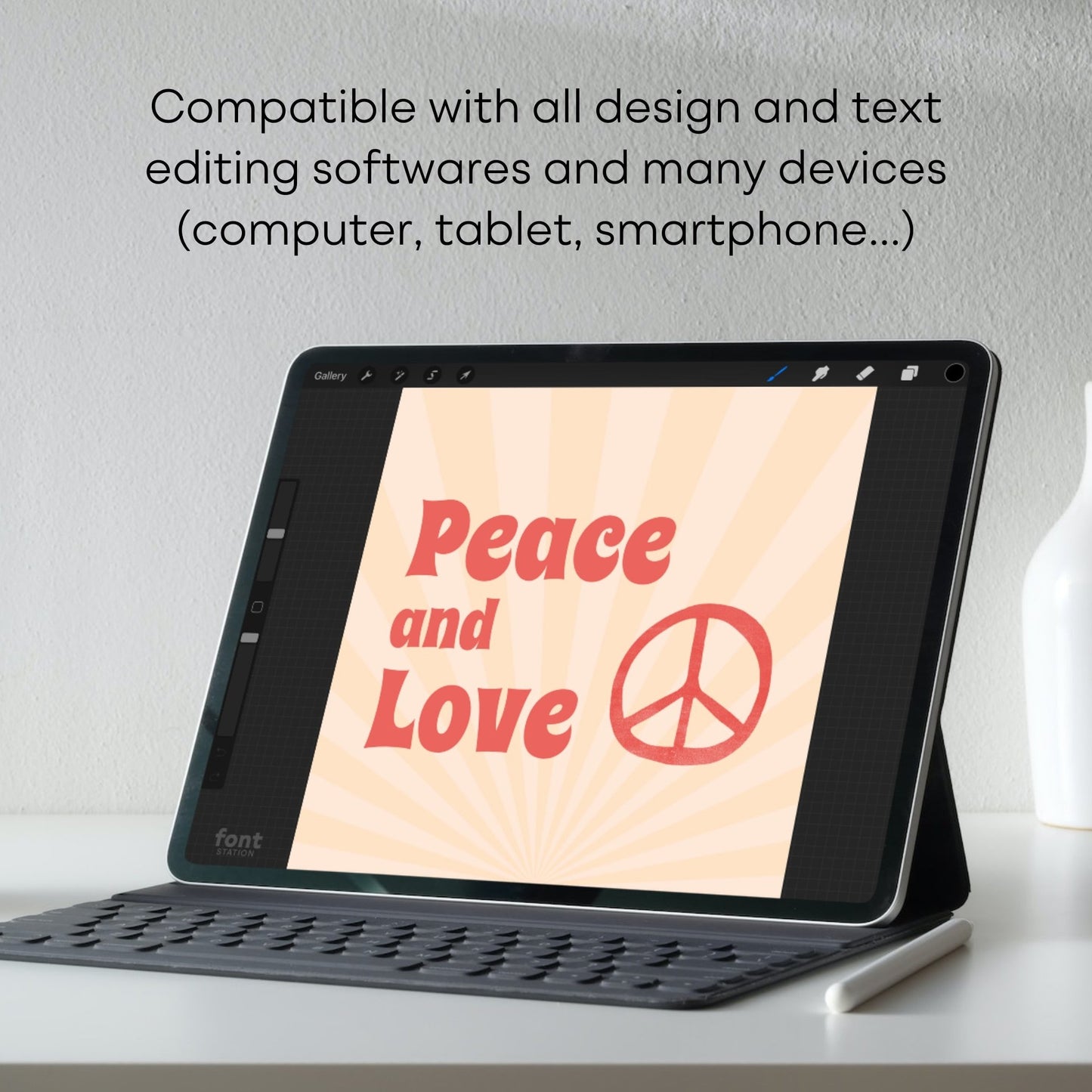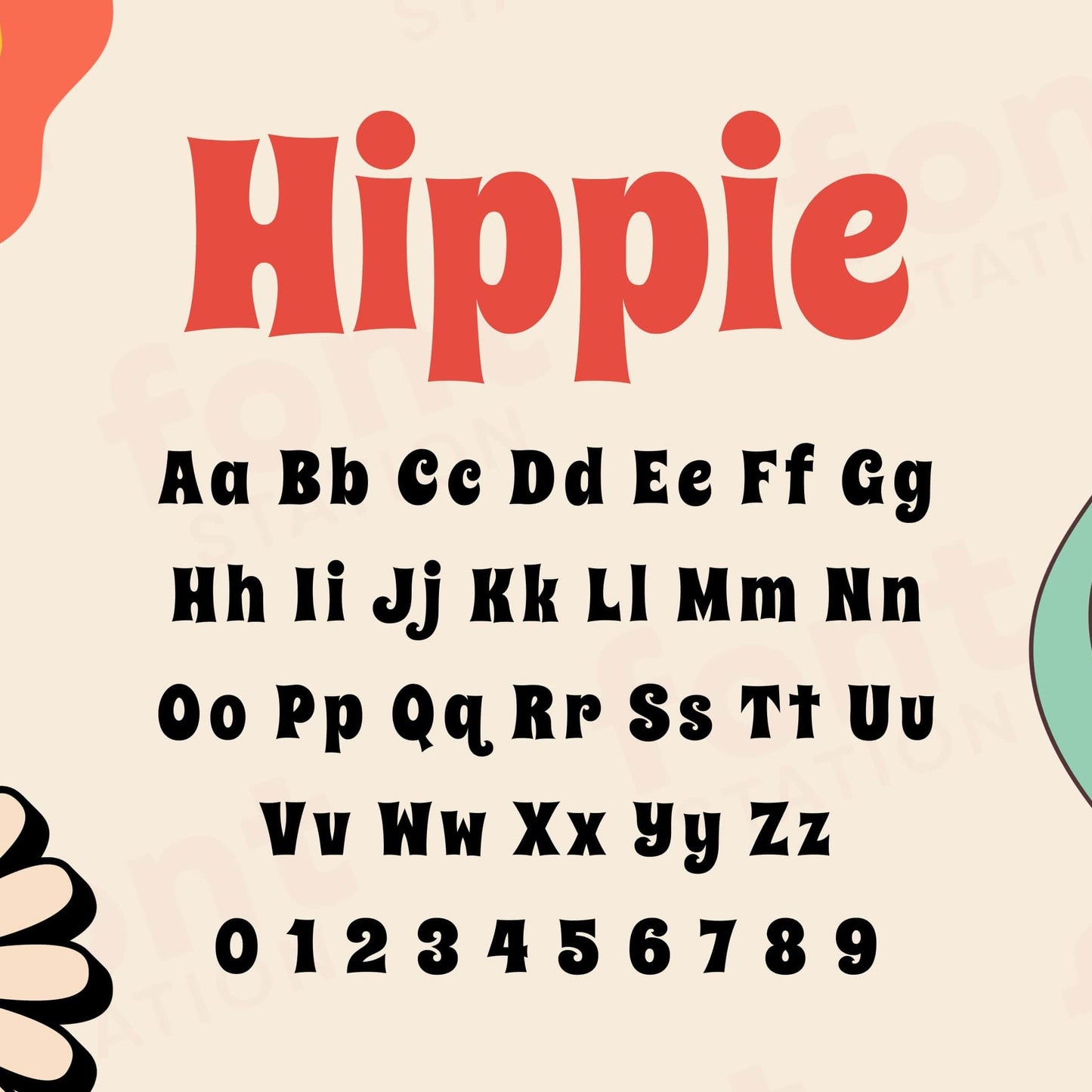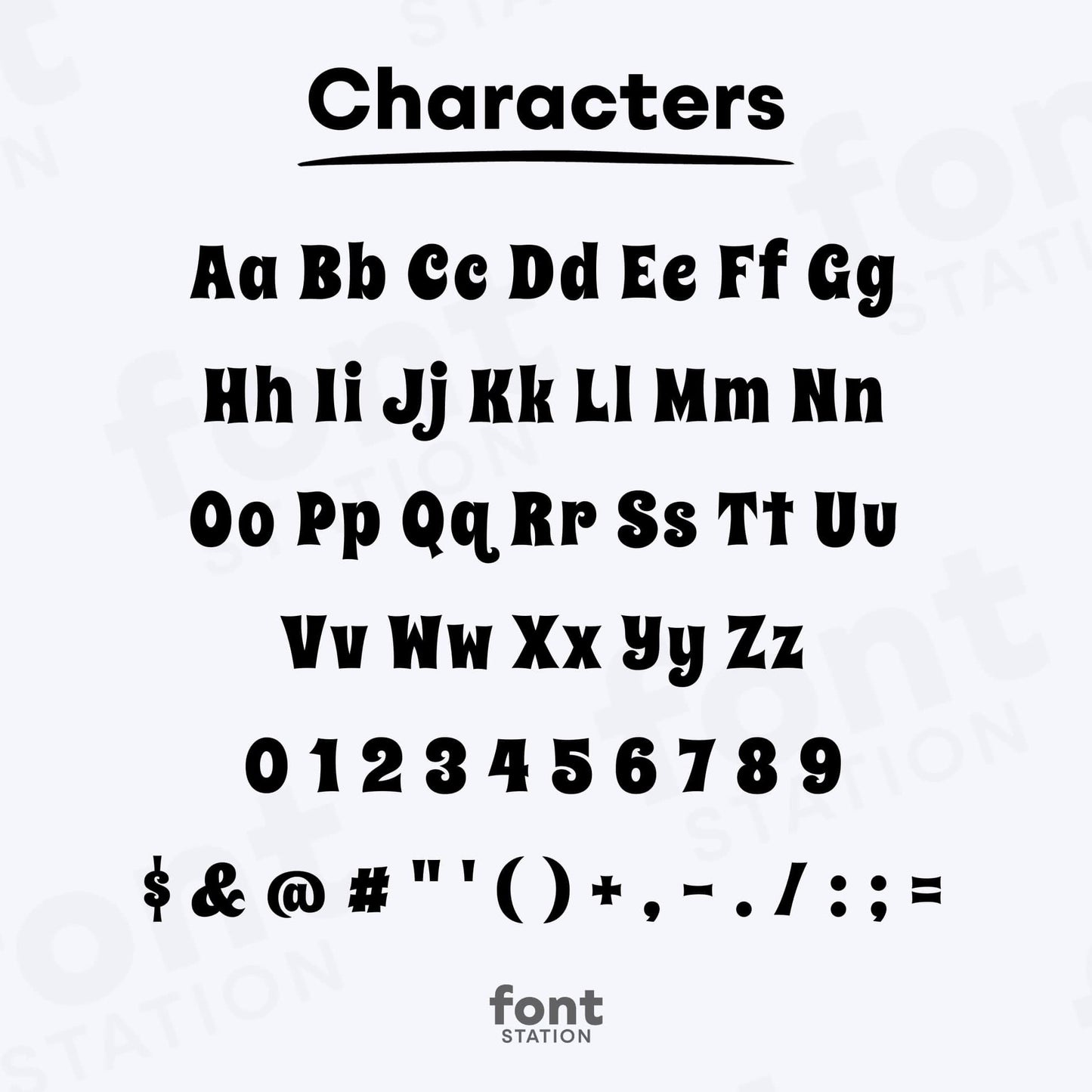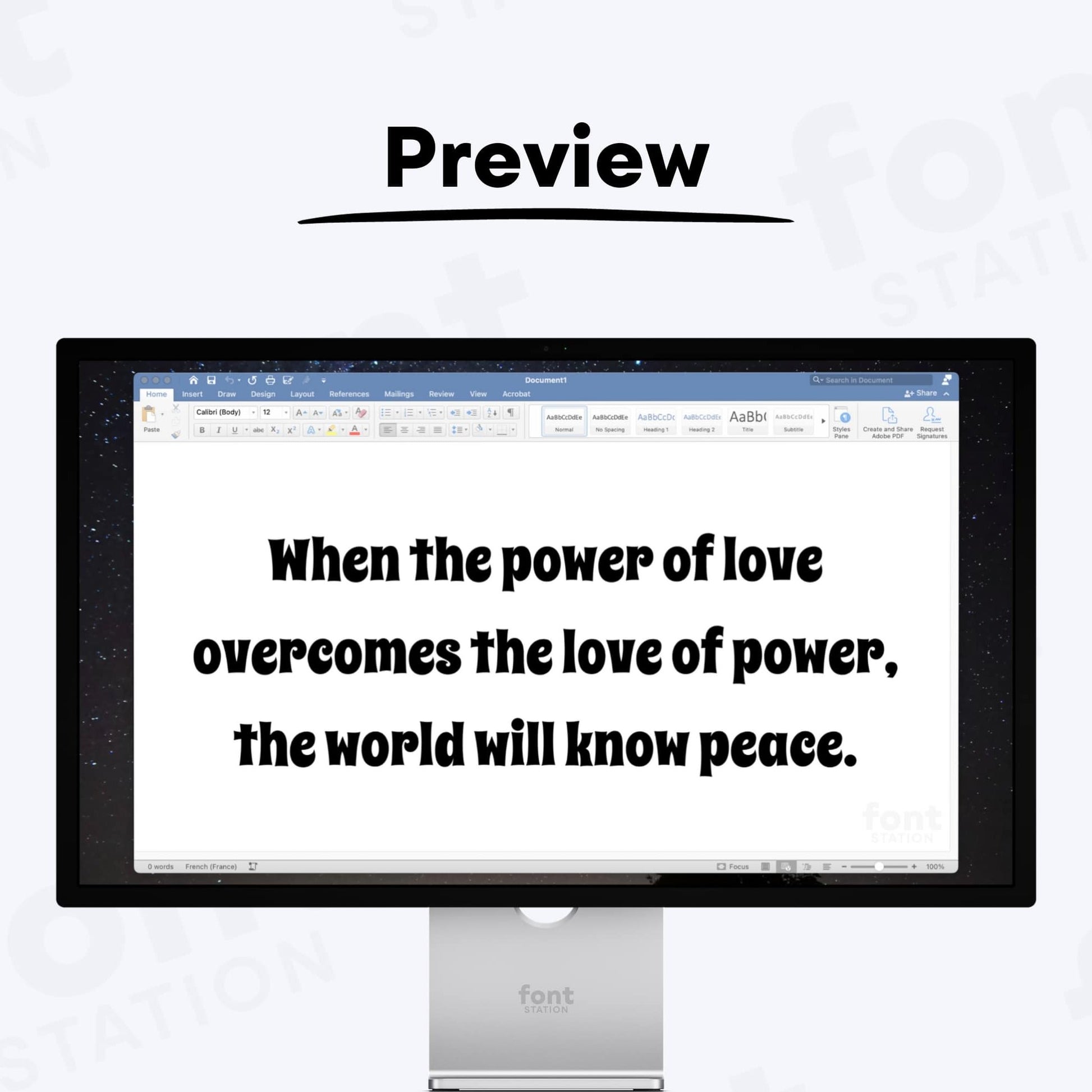
Hippie Font
Nuestro tipo de letra Magic Groovy, inspirado en la fuente Hippie
Libera tu creatividad con nuestra fuente Hippie: ¡Una fuente versátil que puedes utilizar en cualquiera de tus proyectos!
¡Coge tu ordenador, tableta u otro dispositivo y empieza a crear ahora mismo con nuestras letras de fuente Hippie! Nuestra tipografía Magic Groovy está inspirada en la fuente Hippie, por lo que es ideal para diversas creaciones digitales (logotipo, palabra...), sublimación, adornos para tartas, pegatinas, decoración de eventos y mucho más.